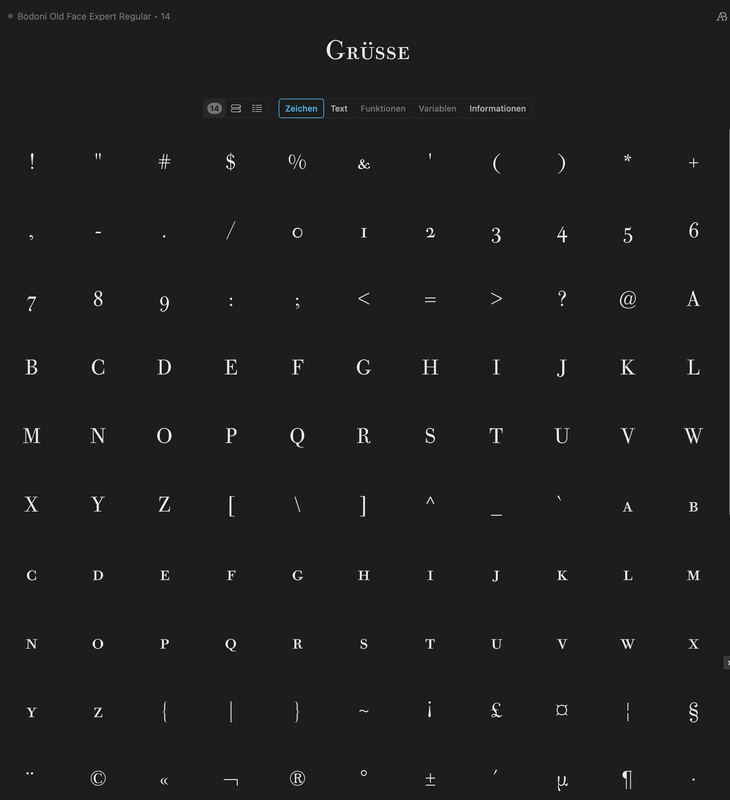
Text und Titelprägung - Müssen die Schriftarten aufeinander abgestimmt werden?
Ich bin Hobbybuchbinder und habe jetzt schon einige Male Romanmanuskripte zu Büchern gebunden und sie auch mit Titelprägung versehen. Die Manuskripte wurden mit LaTeX erstellt, dessen Defaultschrift mir nicht so gut gefällt und ich habe den Font deswegen in Palatino geändert. Ich mag irgendwie die gewisse Leichtigkeit, die diese Schrift vermittelt. Der gesamte Text ist in Palatino gesetzt - inklusive Titel, Kapitelüberschriften etc.
Wenn es um die Prägung geht, ist man natürlich sehr eingeschränkt. Prägeschriften sind ja sehr teuer und für den Amateur im Grunde fast nur gebraucht zu bekommen - außerdem ist das Angebot inzwischen sehr beschränkt. Inzwischen habe ich drei Schriften zur Auswahl: Einen Satz "Reform Grotesk", den mir @Ralf Herrmann dankenswerterweise als solchen bestimmt hat mit einer Versalienhöhe von ca. 11 mm, einen Versaliensatz "Steinschrift" mit ca. 6 mm Höhe und einen Satz "Bodoni Antiqua" mit ca. 5 mm Höhe.
Was ich nun tue ist, den Titel des Buches in "Reform Grotesk" und den Verfassernamen in "Steinschrift" zu prägen. Es ist selbstverständlich nicht dieselbe Schriftart, aber es setzt aus meiner Sicht einen guten Kontrapunkt zur Serifenschrift im Inneren des Buches.
Frage nun an die Experten: Ist mein Denkansatz richtig? Oder ist es aus Eurer Sicht nicht notwendig, die Schriftarten von Text und Titelprägung aufeinander abzustimmen?
Ich hatte auch überlegt, den Text des Buches komplett in Bodoni umzusetzen, was sogar dazu geführt hätte, dass das Buch ein paar Seiten kürzer geworden wäre. Aber der Anblick der Bodoni für den Textkörper tat mir in den Augen weh. Das ist aus meiner Sicht eine Schriftart, die man nur für Überschriften verwenden kann.
Nachtrag: Was ich bei der Bodoni darüber hinaus vermisst habe und sie deswegen nicht für den Text nutzen wollte, sind Mediävalziffern und (obwohl ich sie nur sehr wenig benutze) Kapitälchen.
Ich hatte schon historische Bücher aus dem 18./19. Jahrhundert in der Hand die in einer Bodoni gesetzt waren. Durch die damalige Drucktechnik und die Papierqualität gab es einen deutlichen Quetschrand und einen entsprechenden Tonwertzuwachs. Die feinen Details die die Bodoni in modernen Druckverfahren hat waren damals deutlich weniger ausgeprägt und die Lesbarkeit dadurch besser. Der technische Fortschritt hat die Bodoni sozusagen zur Displayschrift degradiert.
Es gibt ja nicht »die« Bodoni, sondern unzählige. So findet sich auch eine Bodoni mit SC und Mediävalziffern, z.B. die »Bodoni Old Face Expert«:
Dort sind dann aber keine Gemeinen enthalten.
Hallo. Die Old Face Expert wäre natürlich eine Möglichkeit. Aber ich weiß nicht, ob sie für LaTeX verfügbar ist. Aber wenn das so ist, könnte man das sicher hinfrickeln. Aber wie gesagt: Mir gefällt die Bodoni für den Textkörper nicht. Deswegen würde sich die Mühe nicht lohnen. Aber es ist trotzdem gut zu wissen, dass es dieses add-on gibt...
LaTaX kann meines Wissens nach mit allen (modernen) Schriftformaten umgehen, also auch .ttf- und .otf-Fonts. Ich habe jetzt auf die Schnelle folgende Seiten gefunden, die Dir eine Lösung oder zumindest einen Startpunkt zeigen:
notwendig ist das sicher nicht. Es ist sogar auf dem Buchmarkt Standard, dass Umschlag und Inhalt gestalterisch nicht aufeinander Bezug nehmen. Das liegt aber nicht daran, dass das gute Sitte wäre, sondern dass mit dem Innenteil in den allermeisten Fällen Setzer beauftragt werden, während der Umschlag davon unabhängig von Marketern gemacht wird – und für die zählen in erster Linie die KPIs ihrer Dashboards; gute Gestaltung an sich hat keinen Wert (wir reden hier jetzt vom Gros des Buchangebotes und nicht von irgendwelchen Hermann-Schmidt- oder Slanted-Büchern, klar). Ein Buchdesigner im eigentlichen Sinne würde aber das gesamte Produkt aus einem Guss sehen wollen.
Gerade, wenn du die Bodoni in Schaugrößen für den Umschlag/Titel einsetzt, kannst du in Lesegrößen problemlos auf eine andere klassizistische Antiqua umsteigen. Es gibt inzwischen viele Serifenschriften dieses Genres, die für Brottext tadellos geeignet sind (wie @Microboy schrieb, hier gilt es vor allem den Strichstärkenkontrast zu verringern, damit keine Details wegbrechen). Dafür kommen zum Beispiel Monotypes Walbaum Pro 06Pt bzw. Walbaum Pro 12Pt in Frage oder vielleicht sogar die Questa oder am besten Allrounder Didone. Dave Lawrence (California Type Foundry) hat außerdem Bodoni Casale gezeichnet, eine robustere Bodoni nach Giambattista Bodonis Originalentwürfen, aber wie gut die im Mengentext funktioniert, kann ich nicht sagen.